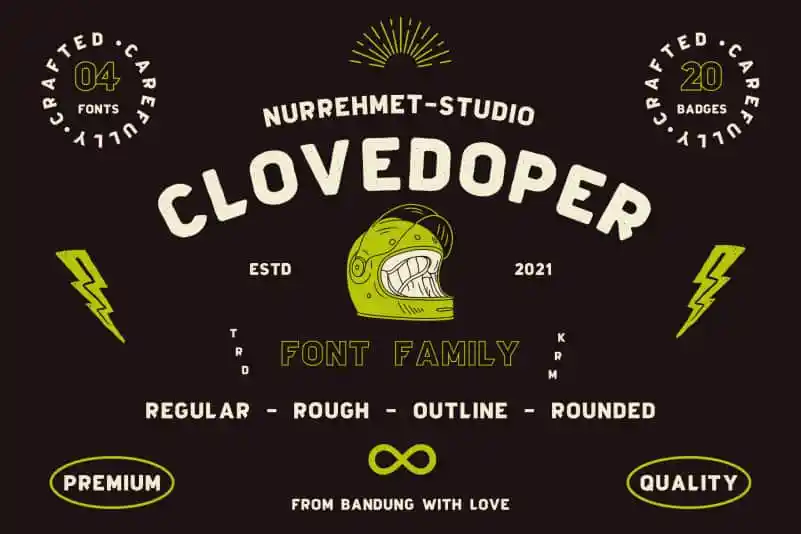
A Clovedoper Font é uma novidade que combina características de letra com pacotes de modelo e cartaz para atender a um público moderno e vibrante. Ela traz uma sensação leve e estilizada, ideal para empresas customizadoras de garagens, clubes de motocicletas ou pessoas apaixonadas por esta paixão urbana. Esse font é perfeito para criar identidades visuais memoráveis, seja no formato de logotipos, roupas personalizadas, arte impressa, cartões de visita ou materiais de marca. Também oferece uma gama incrível de possibilidades quando se trata de imagens naturais e fotografias de natureza. Através de sua cuidadosamente elaborada construção, a Clovedoper Font permite que as suas ideias ganhem vida em diferentes formatos de mídia digital ou impressa.